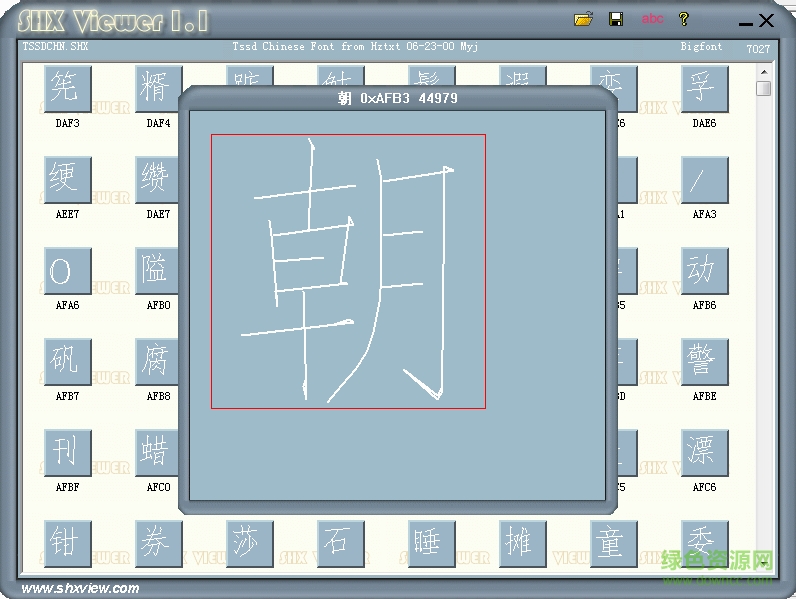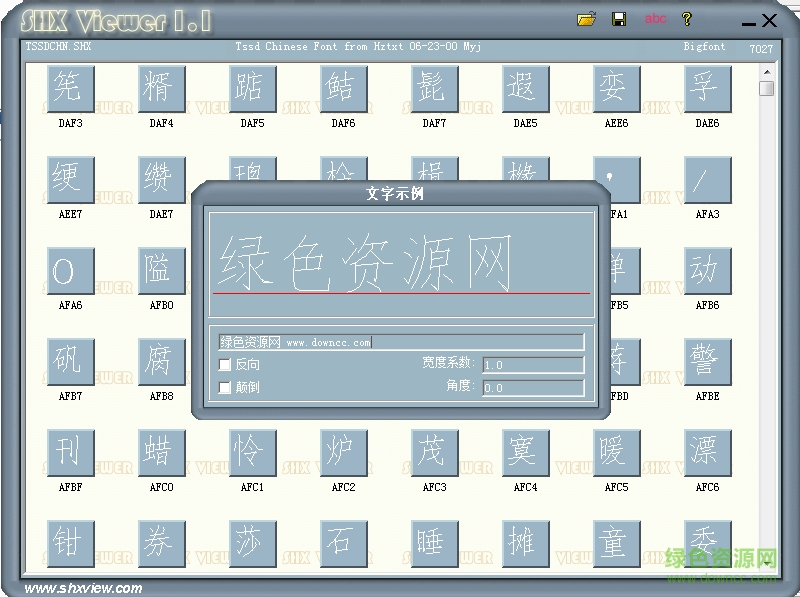
atssdchn.shx是一款擁有7027個(gè)字符的cad字體,字跡飄逸灑脫,很有古風(fēng)韻味,字庫豐富覆蓋交廣,流暢的字形和簡約的筆觸讓人很有視覺好感,綠色資源網(wǎng)歡迎大家免費(fèi)下載!
atssdchn.shx可能是tssdchn.shx字體被其他用戶私自修改名稱后的字體,tssdchn.shx是一款可以解決大部分鋼筋符號(hào)亂碼的autocad字體。